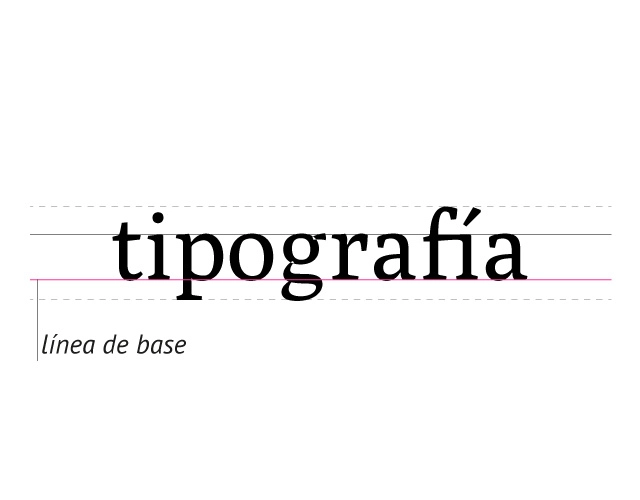
LÍNEA DE BASE
Es la línea horizontal en la cual se apoyan los signos tipográficos. Algunos signos se apoyan flotando por encima de esta línea (como “las comillas”), otros tienen elementos por debajo (como los descendentes), pero es una línea de referencia desde la cual se diseña el apoyo de todos los signos de una familia tipográfica. Algunos signos requieren de un ajuste óptico en su posicionamiento sobre la línea de base, como en el caso de los signos con curvas (la “o”, “c”, “u”, “e”, entre otros).